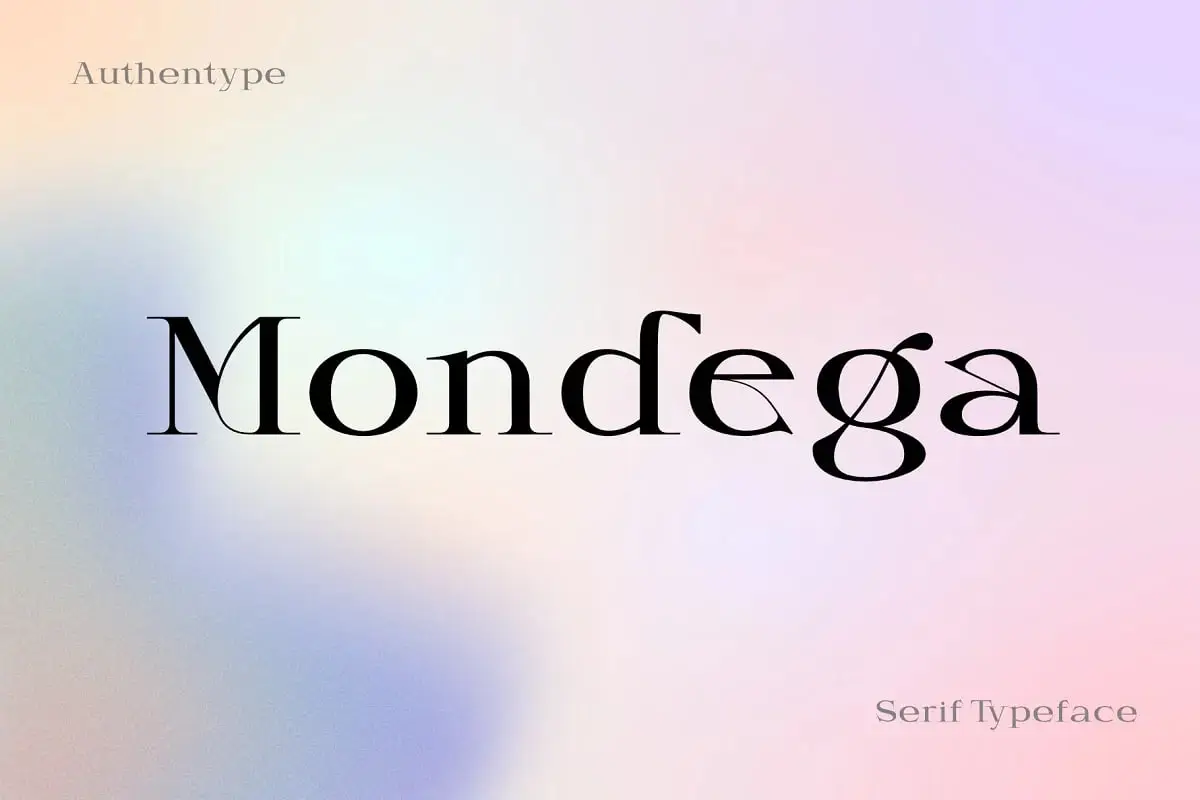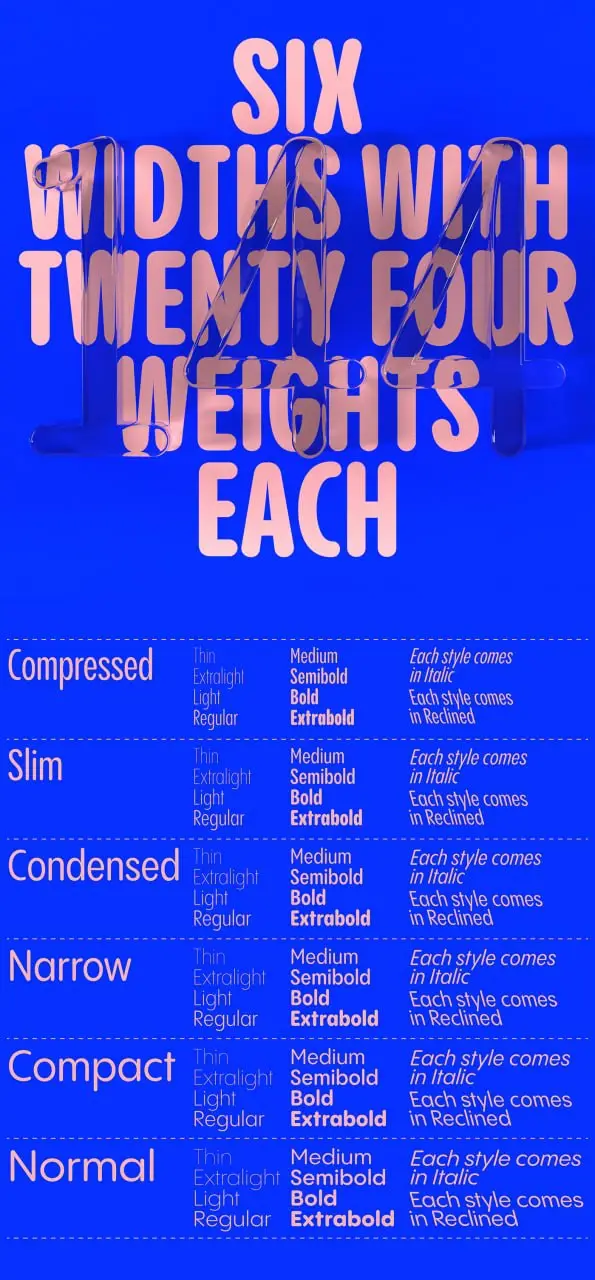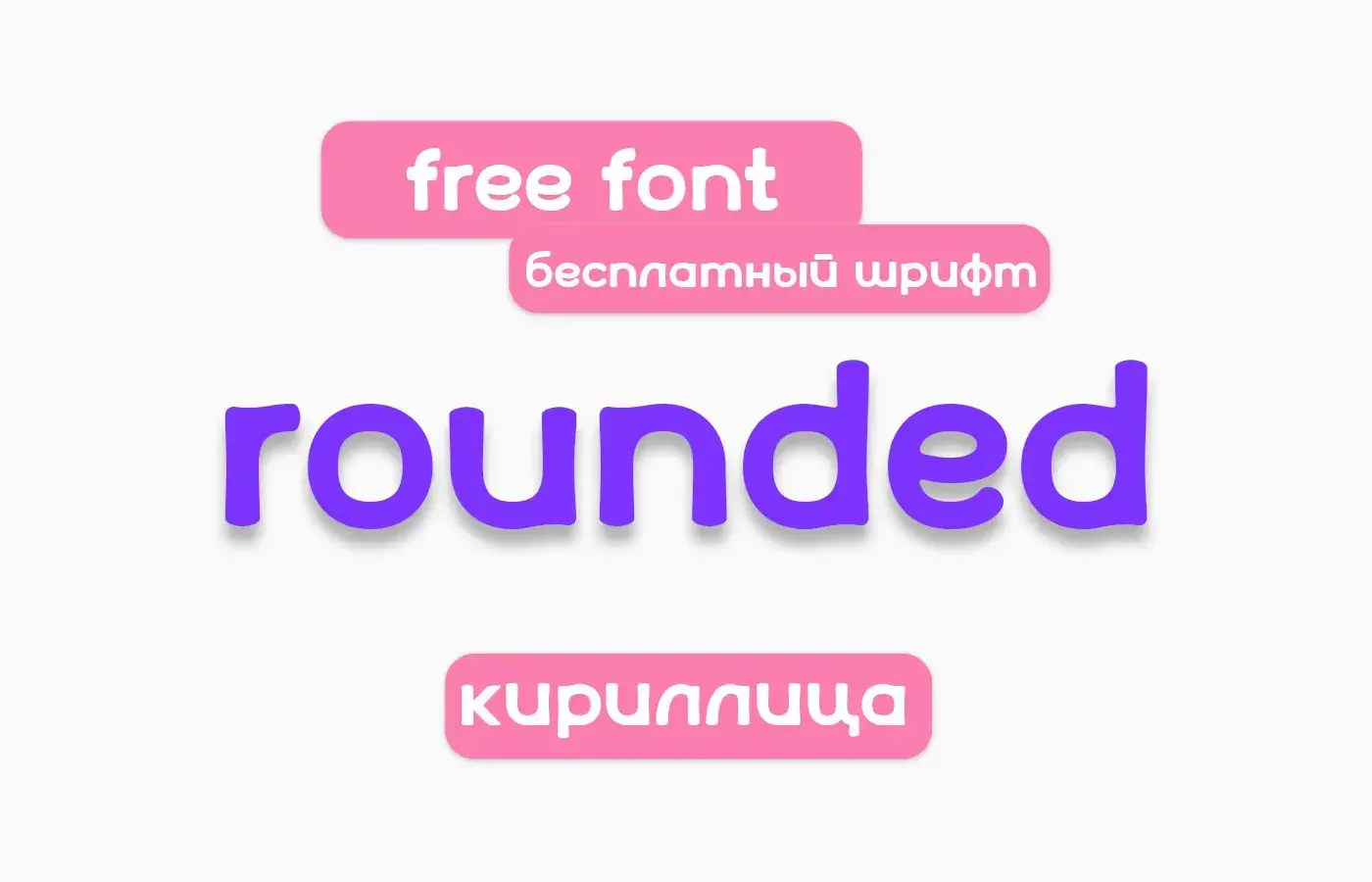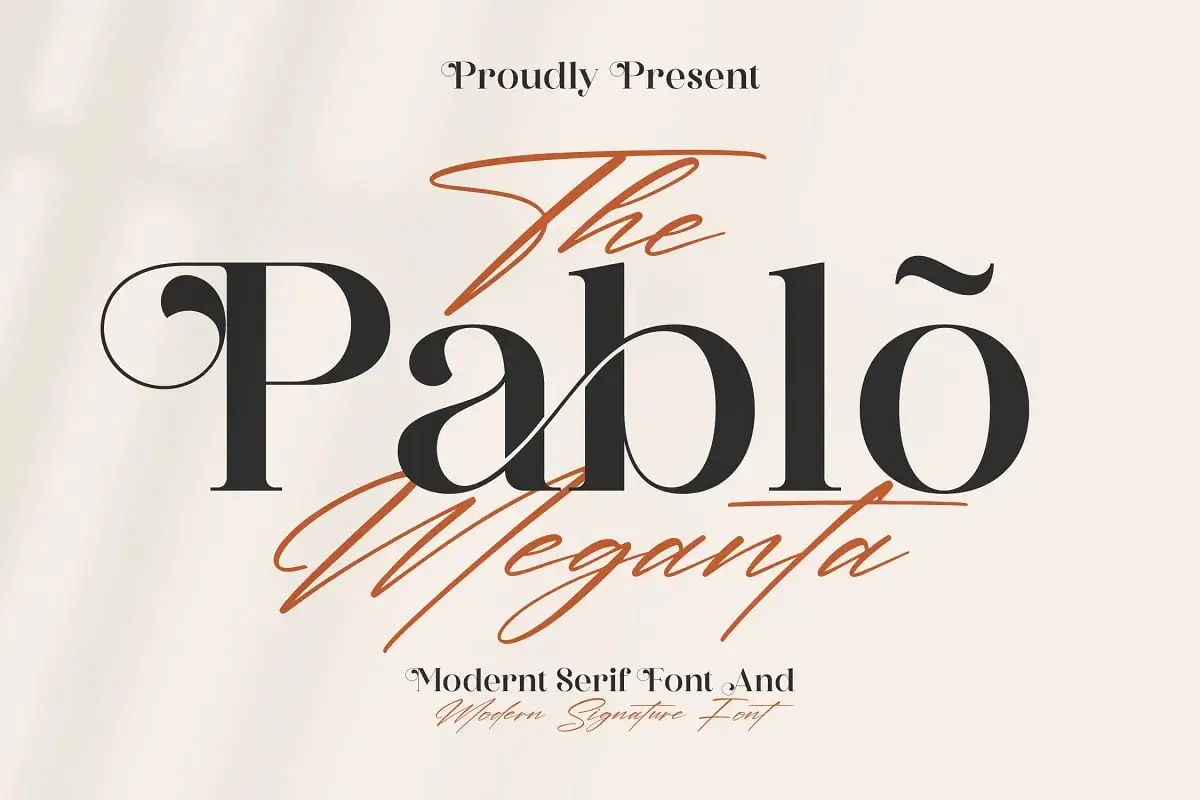
Taiyo™ Serif Font Medium
Taiyo是您追求简洁经典优雅风的不二之选!🌟无论是品牌设计还是编辑排版,其中等字重都在醒目与含蓄之间取得了完美平衡。您会喜欢它在任何尺寸下的清晰可读性!
Pablo Meganta 字体双人组
两种字体,无限可能!🎉 Pablo Meganta 将粗体无衬线字体与流畅手写字体完美搭配——堪称双人组合的典范!它既现代又优雅,是制作标志或社交媒体魔力的绝佳选择。
Roman Barygin 设计的 Snfbstrd
哇,这款太独特了!🦄 Snfbstrd 是创意设计元素的狂野组合,尽显个性。高分辨率且极易自定义,完美为您的数字作品增添“惊艳”效果。
Seraya 字体
优雅兼具现代感!✨ Seraya 独特的字形与干净利落的线条,是品牌和标志设计的绝佳之选。提供常规、粗体或斜体版本——你的项目将瞬间提升格调!
Red Script Pro 字型 (C) Rodanthi Senduka
Red Script Pro Typeface (C) Rodanthi Senduka
这款手写字体是纯粹的流动优雅!💃 Red Script Pro 像诗歌一样流畅,为任何设计增添奢华感。多种字重意味着它既美观又实用——非常适合请柬或品牌设计。
复古风情
怀旧风尚
是否感到怀旧?🕰️ 怀旧风尚是一套精美的复古风格图形与插画集,能为任何项目增添温暖与魅力。高质量且易于使用——超级心动!
框架
Ramka
Ramka 是您追求清晰、干净视觉效果的新好帮手!🔲 高分辨率且高度可定制,这些设计素材能无缝融入您的工作流程。适用于个人或商业用途!
Rounded
柔和、友好,且现代感十足!🟣 Rounded 带来一系列温和的形状和元素,让你的设计显得亲切而温暖。品质出众,玩起来超级有趣!
Mondega-现代衬线字体
Mondega-Modern Serif Font
Mondega 是你梦想中的现代衬线字体!🎯 干净、现代,提供多种字重,无论是网站标题还是奢华印刷品都完美适用。千万不要错过这款!
Nomerok Mono 作者:Mikhail Mmaikonyan
Nomerok Mono By Mikhail Mmaikonyan
各位编码爱好者和UI设计师请注意!💻 Nomerok Mono是一款时尚的等宽字体,既清晰易读又充满格调。多种字重使其同样适合品牌设计——简洁且统一!
Preta-© 2014 由 © Maximiliano R. Sproviero Lian Types 设计
Preta-© 2014 By © Maximiliano R. Sproviero Lian Types
Preta 是一款当代惊艳之作!🌟 由 Maximiliano R. Sproviero 设计,这款字体拥有清晰的线条和多种字重,灵活性十足。无论是个人项目还是商业用途都非常适合!
Pixesia Studio-Qarlient 字体
Qarlient 字体将现代与经典风格巧妙融合,堪称大师级作品!🎭 它完美适用于品牌设计、标志制作和网页设计,支持多种语言,并提供多种字重。灵活性做到了极致!
Power Display 字体 — 作者:Teguh Arief Power Type
Power Display 字体 - 作者:Teguh Arief Power Type
想要吸引眼球?🗣️ Power Display 字体粗犷醒目,充满冲击力。专为标题和宣传素材设计,带给你渴望的“看我这里”的能量!
Nouvelle Noire Rektorat 字体家族
Nouvelle Noire Rektorat Font Family
优雅与多用途的完美结合!🖤 Nouvelle Noire Rektorat 提供衬线体和无衬线体两种变体,并支持多种字重。高可读性与优雅曲线,是品牌设计的理想之选!
Potra
Potra 是创意专业人士的必备之选!🎨 多种风格的高分辨率图形,定制超简单,兼容所有主流设计软件。立即提升您的项目吧!
Pangram Sans Rounded 字体
Pangram Sans Rounded-Font
Pangram Sans Rounded 是当下最友好的字体!🧸 它柔和圆润的边缘,使其非常适合现代、亲民的设计。多种字重、大写字母、数字——一应俱全!
Luuna 作者:Tatyana Korenivskaya
Luuna By Tatyana Korenivskaya Luuna
Luuna 为您带来独特梦幻的美学体验!🌙 高品质数字资源,风格多样——易于自定义,完美提升任何视觉内容。
Mistont
Mistont 是你未曾察觉却必备的多功能素材!🌫️ 高品质、可定制,完美适配任何创意主题。将它加入你的工具箱,见证设计的蜕变吧!
Mauren 字体
Mauren Font
Mauren 是优雅的化身!👑 凭借其独特的字形和匀称的比例,这款字体是品牌和标志设计的瑰宝。无论数字媒介还是印刷品,它都能完美呈现!
Mn Grissee 字体(Mantranaga Studio 出品)
Mn Grissee 字体 - 出品自 Mantranaga Studio
Mn Grissee 是现代优雅的典范!🖋️ 提供常规、粗体、细体三种字重,并支持 OTF、TTF 和 WOFF 格式,这款字体足以应对你的各种创作需求。简直是灵感满满的创作利器!